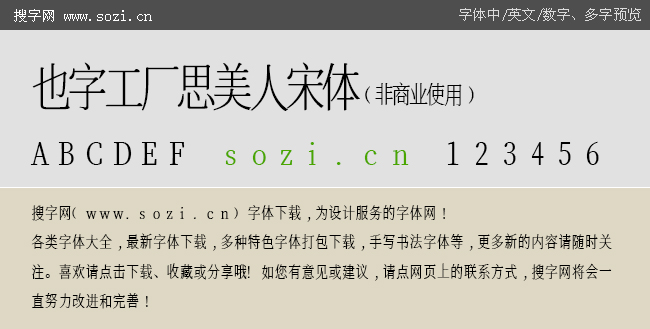
也字工廠思美人宋體
搜字網(wǎng)給大家提供一款也字工廠思美人宋體(非商業(yè)使用)中文字體下載,也字工廠思美人宋體是一款宋體字體,字體優(yōu)雅俊秀,筆畫簡潔大方,具有很好的視覺效果。適合應用于海報設計、包裝設計、網(wǎng)頁設計等應用(此字體為個人非商用版,商用可以聯(lián)系:官方網(wǎng)址:https://yefont.com/home,聯(lián)系方式:13798980448)。